40 новых бесплатных шрифтов
Коллекция из сорока роскошных шрифтов, которая пригодится в работе любому приличному дизайнеру.
Типографика — это не только написание букв и способ передачи сообщения, это еще и способ придать сообщению настроение, бэкграунд и дополнительные смыслы.
Прошлая наша коллекция, мы надеемся, оказалась вам полезной, и вот еще одна. Новые шрифты, сделанные дизайнерами и типографами в минувшем году. По большей части бесплатны полностью, но некоторые доступны в урезанном варианте, что некритично.
Они отражают шрифтовые тренды, они красивы, гармоничны и современны. Да, у большинства из них нет кириллической версии, но, во-первых, в работе нам часто бывает нужна латиница, а во-вторых, эта подборка безусловно способна подарить вдохновение и у нас станет куда больше красивых и гармоничных кириллических шрифтов.
Sequi
Vetka
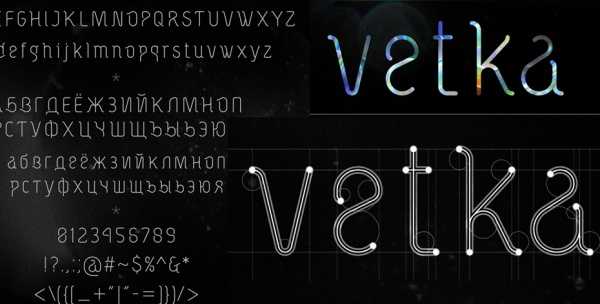
Flex Display Typeface
Barkentina Display Typeface
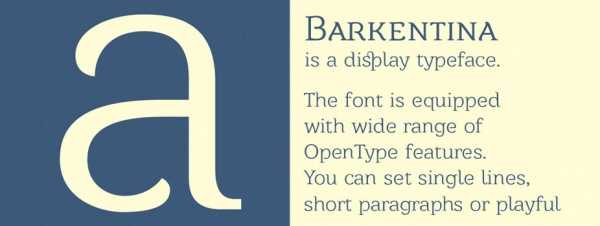
Gabriela
Casper
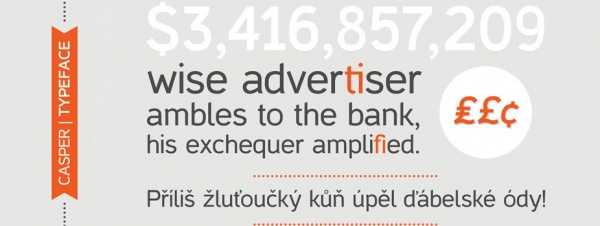
Multicolore Free Font
Sreda Slab Serif
Bellota
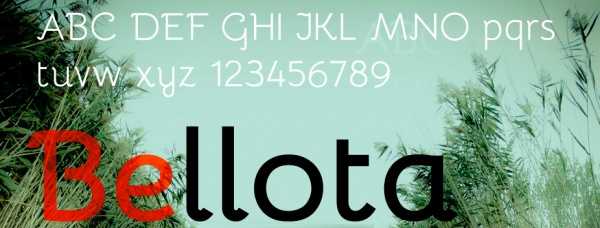
Canter Typeface
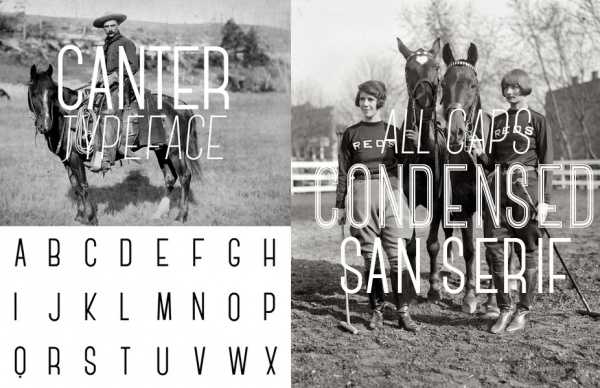
Borgia Pro
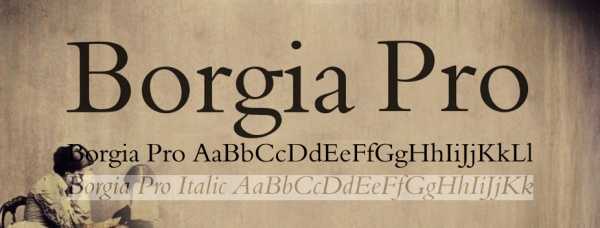
Forum
Signika Sans Serif
Oranienbaum
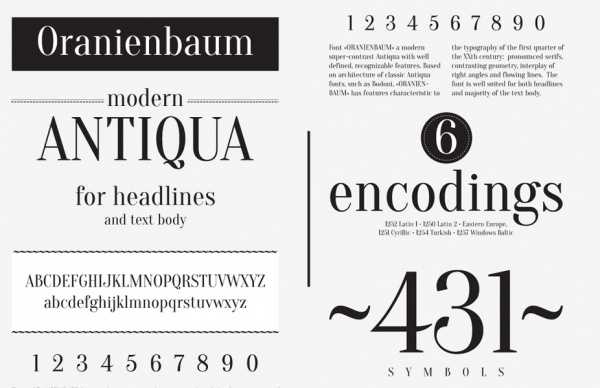
15 дизайнерских кириллических шрифтов
В прошлом посте мы рассмотрели 50 восхитительных дизайнерских шрифтов бесплатно. А сегодня у нас приятный и полезный сюрприз — тоже дизайнерские шрифты, только уже кириллица. Очень часто для работы в рекламных агентствах, или фриланса, и даже для себя нужны красивые шрифты
Бесплатные шрифты для вашего дизайна
И снова вашему вниманию подборка шрифтов. Загляните в вашу коллекцию — не пора ли обновить список любимых начертаний? Дизайнеры советуют не захламлять списки шрифтов, однако и не зацикливаться на уже имеющихся и давно используемых. Возможно в этой подборке вы найдете новые примеры, которые станут достойной заменой старым шрифтам. Все примеры бесплатны. В начале подборки собраны шрифты с кириллической версией, во второй части — только латиница.
Кириллица:
«Берёзки»
TrueLove
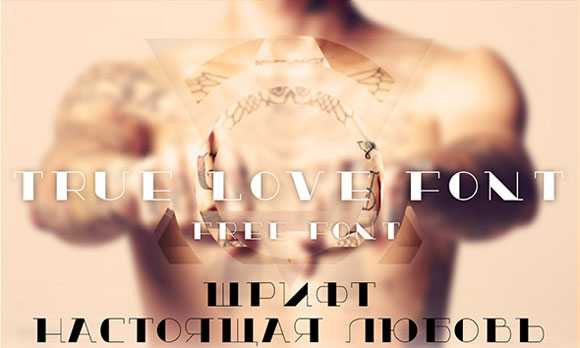
Uni Sans
Sprite Graffiti Font
Intro Condensed
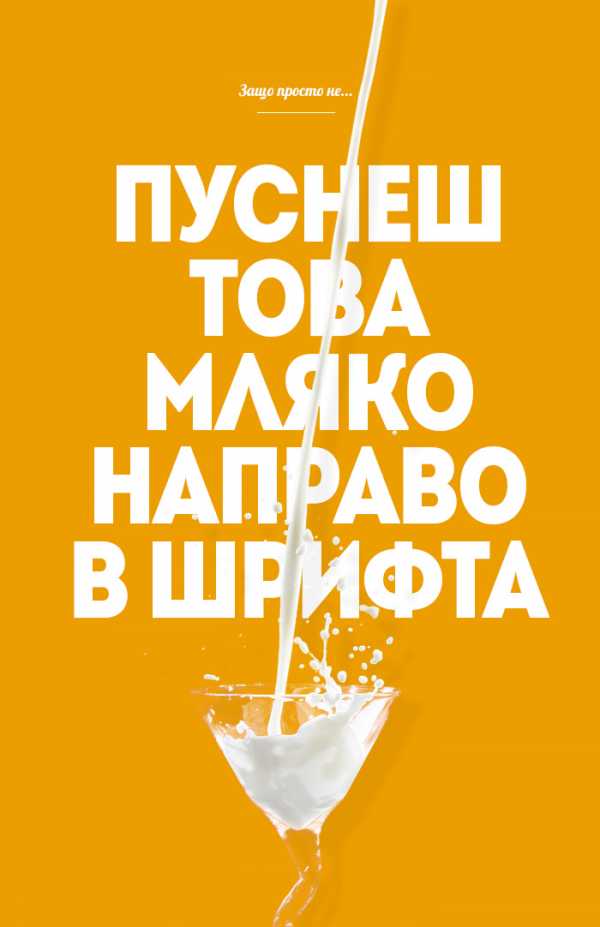
Glober
Bebas
Rounds Black
Teddy Bear
Латиница
Remi Lagast
Raw Font
REN Typeface
Fira Sans
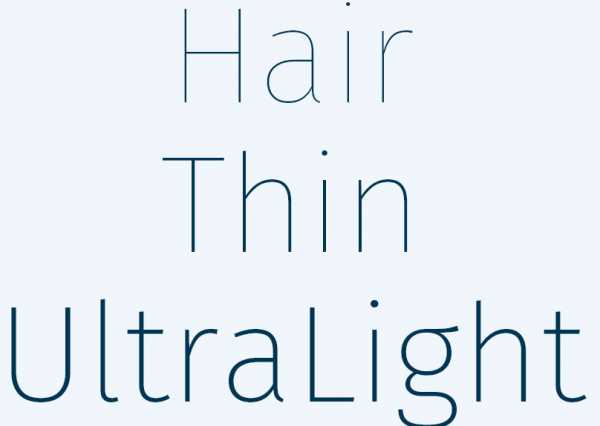
Sinkin Sans
Choplin
SIMPLIFICA
Moderne Sans
Manteka
OSTRICH SANS INLINE